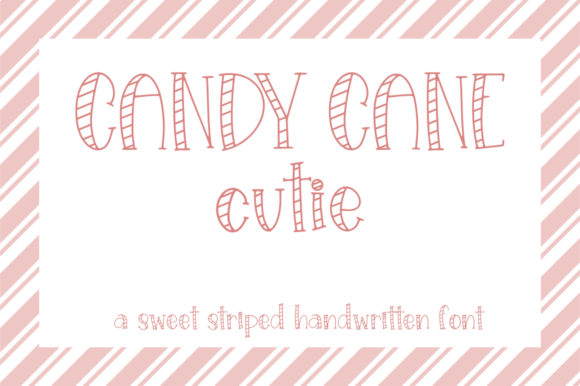
Candy Cane Cutie
適切なデザイン要素を見つけるのは難しい場合がありますが、Candy Cane Cutieは作品を即座に引き立てる優れたコレクションを提供します。
POD(オンデマンド印刷)製品、結婚式の招待状、またはソーシャルメディアのグラフィックを作成している場合でも、Candy Cane Cutieは理想的です。